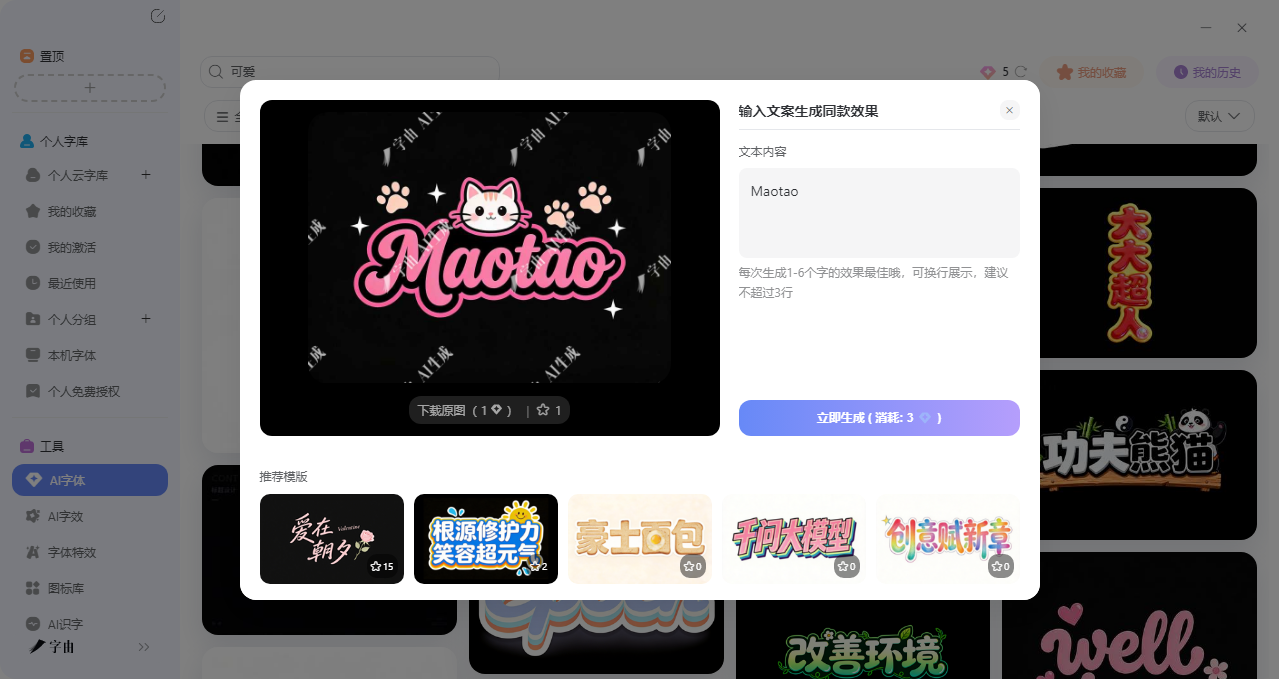
不会画画也能做卡通艺术字?这5个工具帮你一键生成
如果你不想让你的设计画面特别死板,想让本来生动活泼的核心设计跃然纸上?那你肯定要首选的是卡通可爱的字体来衬托你的画面设计,一般会用在生日贺卡、卡通联动、玩偶宣传等,但是在做这种设计的时候缺的往往不是创意和排版思路,而是合适的卡通字体。但是如果自己没有美术功底,手搓出来的字体肯定七扭八歪,其实卡通艺术字一键生成这件事,早就不是什么难事了。今天我就筛选了 5 个亲测好用的卡通艺术字一键生成工具,方便你完成可爱的作品!喜欢的话可以收藏码住先!
第一个要推荐的卡通艺术字一键生成工具是字由。很多人知道字由是字体管理神器,但其实它的AI 字体功能,专门用来生成各种风格的艺术字,卡通风格当然也在其中。
下面我会介绍怎么用字由一键生成卡通艺术字:
第二步:找卡通风格的模板。进入AI 字体页面后,你会看到各种风格的字体模板。想找卡通字体,可以直接点“可爱风”分类,或者搜索关键词“卡通”“可爱”“儿童”。模板库里有很多适合卡通的选项,比如:
- 圆润可爱的泡泡字
- 彩色糖果效果
- 手绘涂鸦风格
- 儿童蜡笔质感
- 萌系动物元素字
每个模板都有预览图,选一个和你设计主题搭的。
第三步:输入你的文案。选好模板后,点击“做同款”,进入编辑页面。在输入框里填你想要生成的文字。需要注意:最好和模板的字数保持一致,这样生成的效果最自然。
第四步:点击生成。确认文案后,点“立即生成”,等25-30秒左右,系统就会输出设计好的卡通艺术字图。生成后可以预览效果。
除了AI生成,字由本身的字体库里也有大量卡通风格字体,而且很多是免费可商用的:
- 点字婴宝:圆润稚趣的可爱字体,适合母婴、儿童、萌宠类设计
- 优设字由棒棒:圆润可爱的风格,比婴宝更活泼一点,适合美食、探店、儿童活动
- 字由面包树:手写感很强的艺术字体,带着一点手工感,适合手作、亲子类主题
- StarLoveSweety:甜美浪漫风格,适合少女心、情侣类设计
2、Fontesh
Fontesh 是一个专门收集免费字体的平台,这个平台我们之前就有介绍过,只不过没有专门讲他有卡通风字体的相关事情,可以看到的是它的首页就有“Cartoon”分类,点进去能看到大量卡通风格字体。我具体推荐的有以下几款字体:
- Chadle Font:粗体有趣的字体,适合做标题
- Super Popstar Font:手写风格,免费商用
- Kindergo Font:手写体,免费商用
- Showpop Font:手写体,免费商用
- Wild Jungle Font:野生丛林风格,适合自然、探险主题
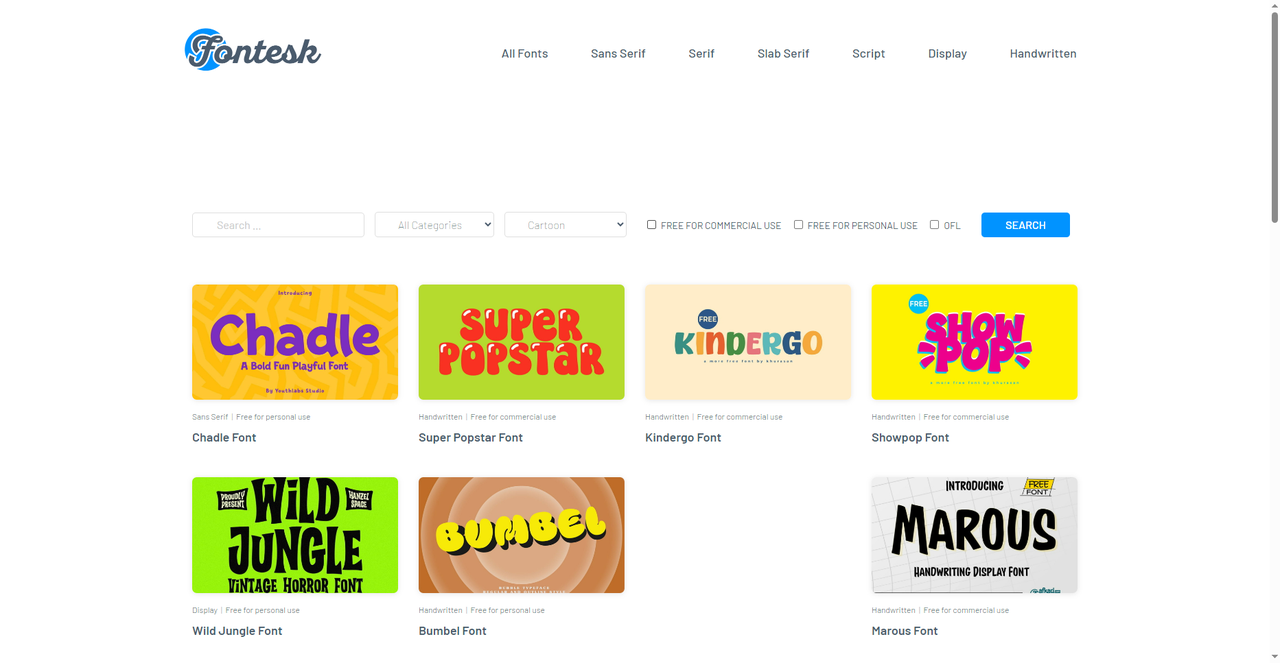
3、Fontspace
在Fontspace 里有11 款精选卡通艺术字体,每款都有详细的预览和下载信息。相关风格标签包括:Cool、Fancy、Cute、Handwriting、Bold、Fun、Retro、Poster、Decorative、Kids、Groovy等。其中比较热门的就是展示的这几款,热度都是从高到低的:
- Superior:由Memet saputra设计,免费个人使用
- Dofed R:由byffoco设计
- Chaplin Type:由cerbond007设计
- Dro:由KC Fonts设计
- Bad Paintjob:由David Kerkhoff设计,做旧涂鸦风格
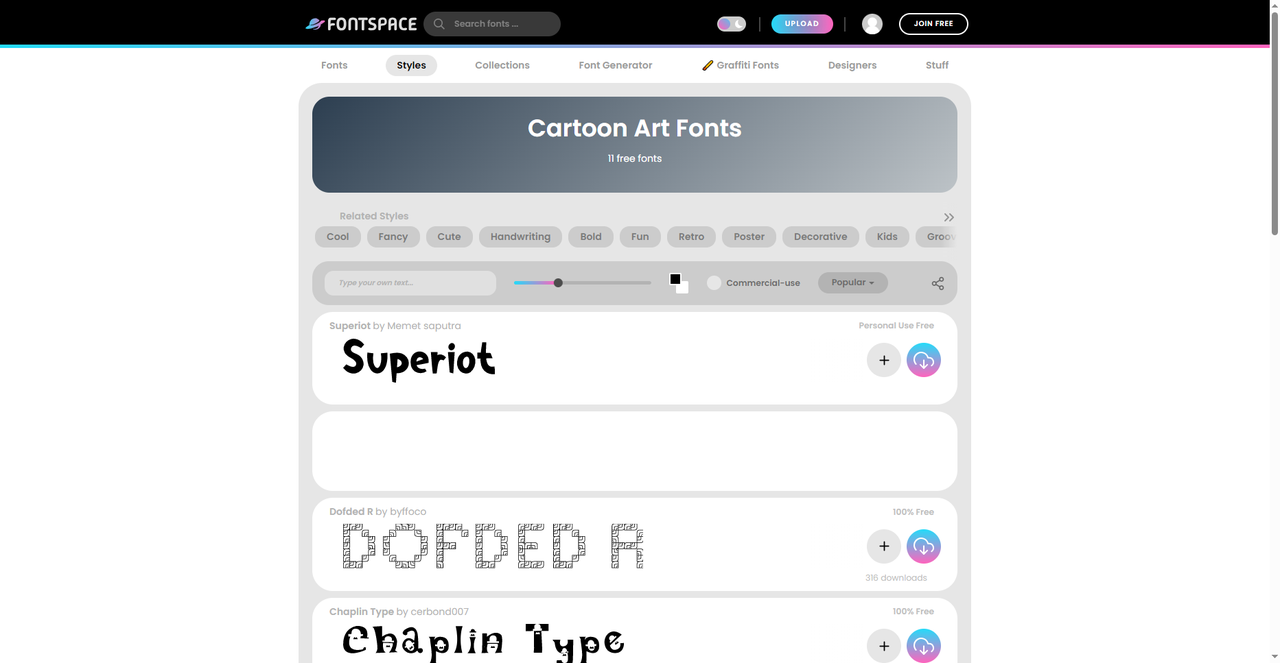
4、71 Free Cartoon Fonts
接下来要介绍的这个字体网站是专门收集卡通风格字体的,目前收录了71款免费卡通字体。它的分类非常细致,你可以按不同维度筛选:
- 按热门程度:3D、Brand、Condensed、Distressed、Graffiti等
- 按字母顺序:A-Z索引
- 按风格:Elegant、Heavy、Red、Stencil等
- 按字体特征:All Caps、Cool、Curly、Dripping、Handwriting、Retro等
没想到吧,一个卡通字体还可以细分这么多分类,这种分类方式的好处是,你可以很精准地找到想要的风格。比如想做复古卡通风,直接点“Retro”;想做涂鸦风,点“Graffiti”。不用在一堆字体里盲目翻。如果你是专攻这方面设计的,这个网站对你来说肯定必不可少,而且网站还提供了字体预览功能,可以输入自己的文字看效果。每款字体都标注了下载次数和授权类型。
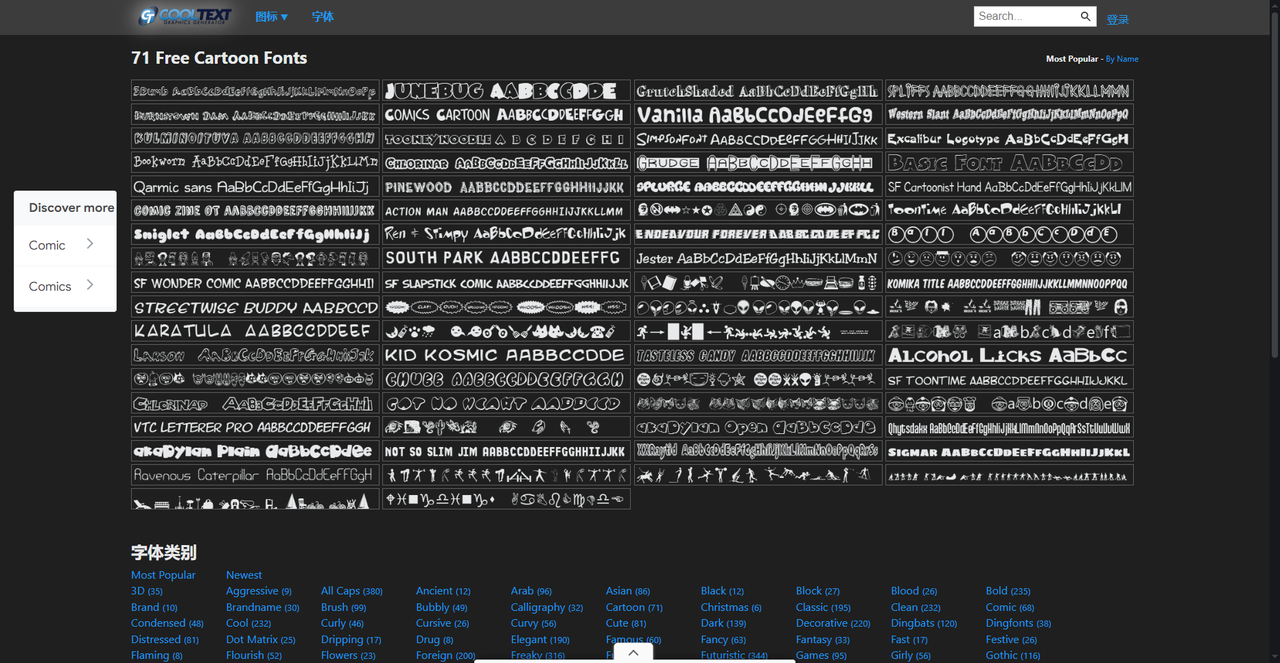
5、DAFONT
这个字体网站在之前我也有介绍过,是涉及方面非常全面的一个知名字体网站,我已经不止在一个博主那里看到推荐了,这些字体大多有免费版本,部分标注了设计师工作室,品质有保证。